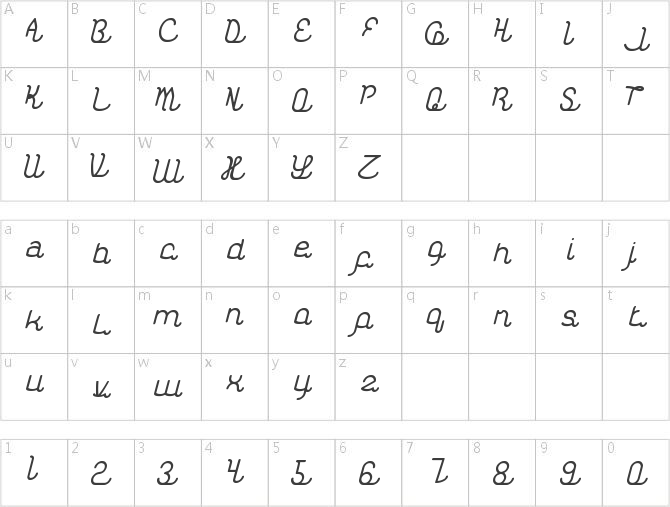
字體名稱(chēng): Kasih D
Kasih Dan sayang-thin
Kasih Dan sayang-thin字體字庫(kù)是一款讓人賞心悅目、百看不厭的英文字體,適合各類(lèi)廣告和產(chǎn)品包裝設(shè)計(jì)應(yīng)用,字體大小0.02MB,格式為ttf字體,上傳用戶(hù)是82年的拉菲,作者/版權(quán)方為未知